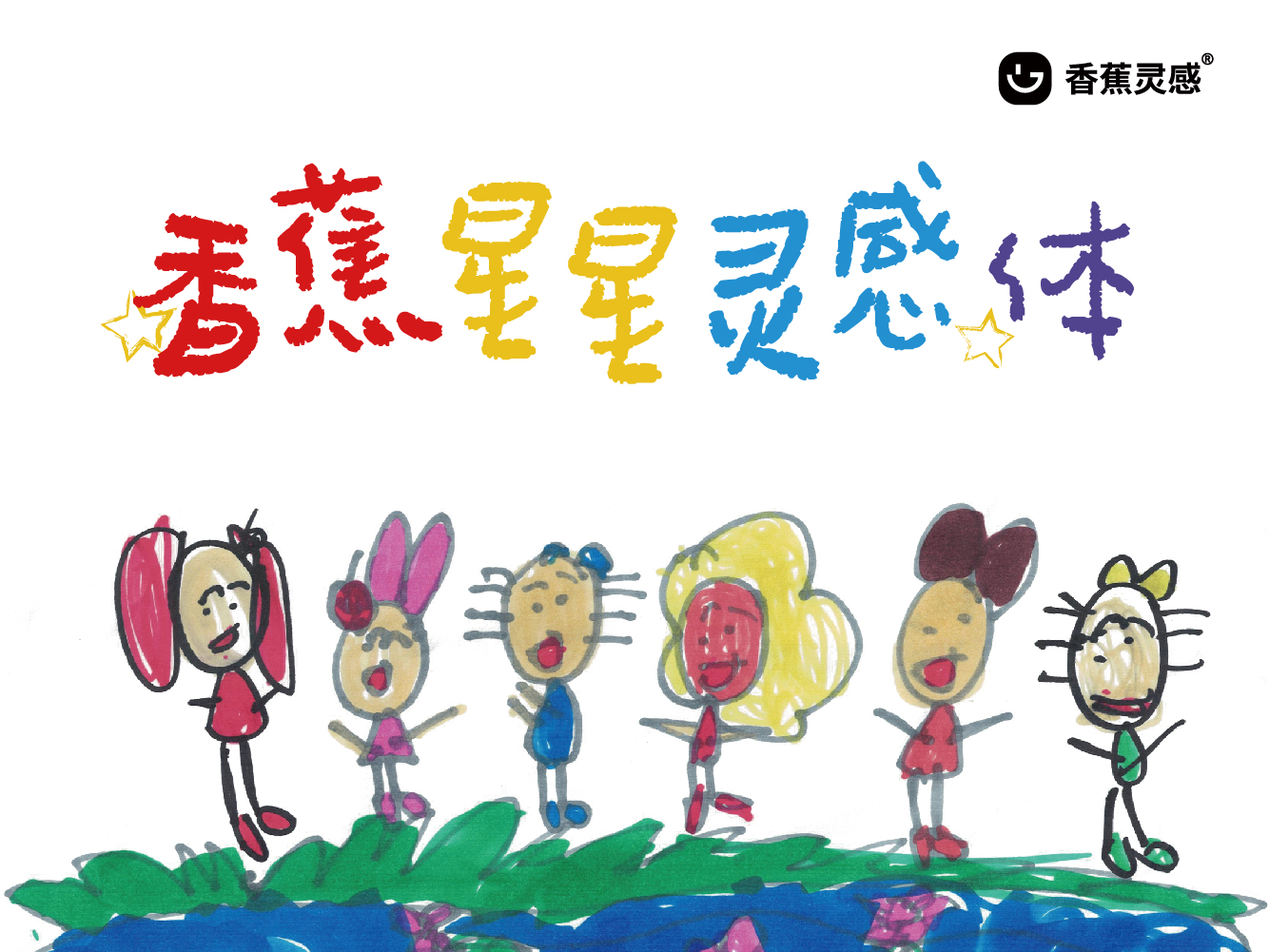
香蕉星星 灵感体
香蕉星星 灵感体,香蕉星星灵感体,设计灵感来自于自闭症儿童的绘画作品,自闭症儿童又被称为“星星的孩子”,他们内心情感丰富,想法天马行空,画作中充满好奇与想象,却甚少被人所理解。香蕉星星灵感体摆脱了笔画的固有角度束缚,省略细枝末节,字型像行走的奇思妙想一般跃动,是一款活泼可爱的创意设计字体。